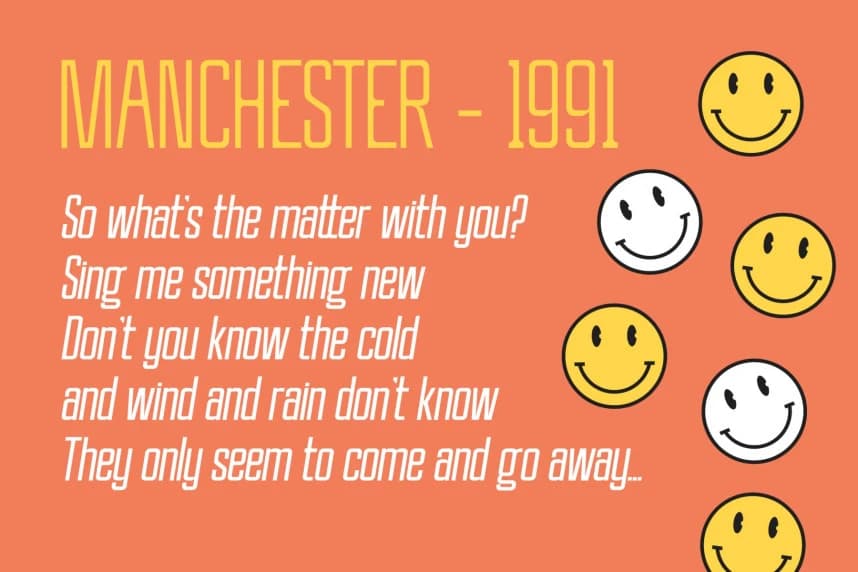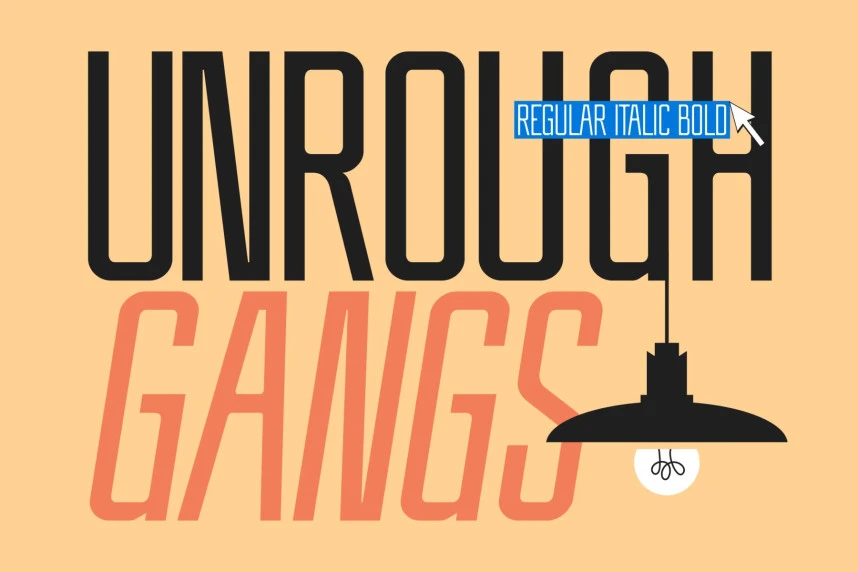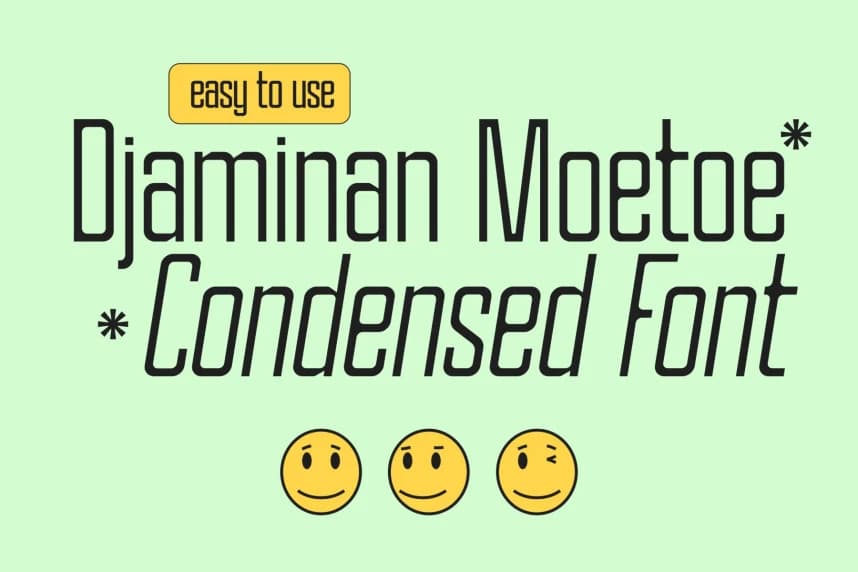
Agira Font, tasarımlarınıza daha özgün bir yön katması için tasarlanmış dar kesimli bir sans serif fontudur. Bu font Regular, Italic, Bold ve Bold Italic sürümlerinden oluşur; çok dilli desteğe sahiptir ve alternatifler ile ligatürlerle birlikte gelir.
Agira Font, tasarımlarınıza daha benzersiz bir yön kazandırmak için özel olarak tasarlanmış dar bir sans serif yazı tipidir. Bu yazı tipi Regular, Italic, Bold ve Bold Italic fontlarından oluşur; dilleri destekler, alternatifler ve ligatürlerle birlikte gelir.